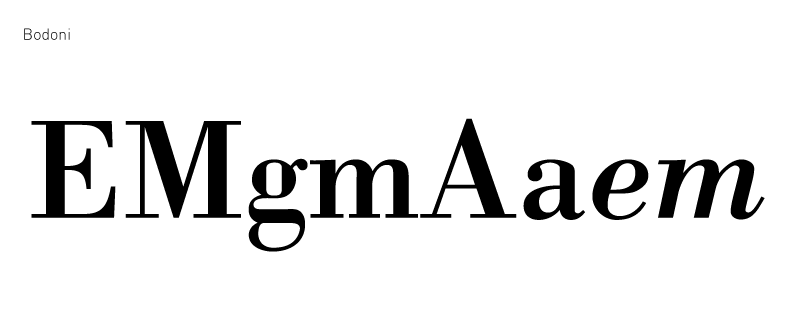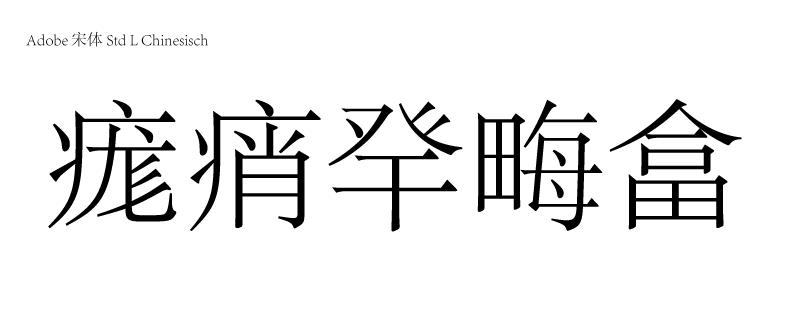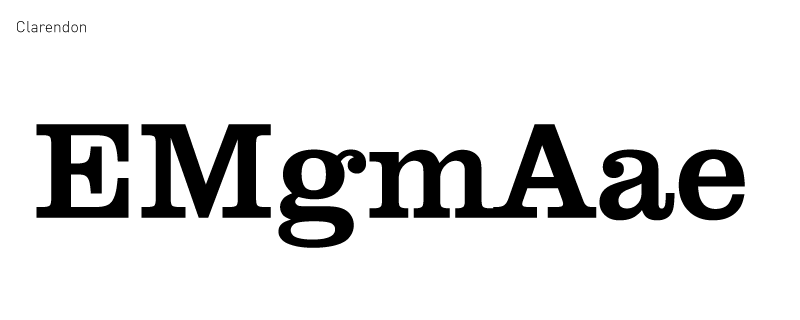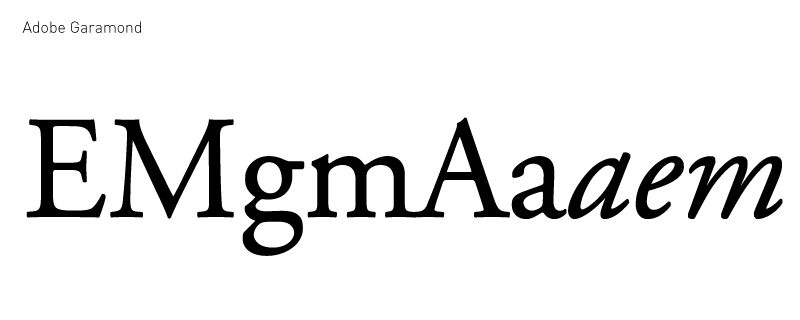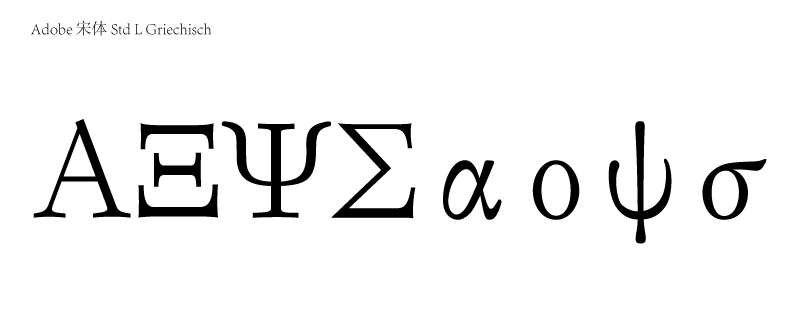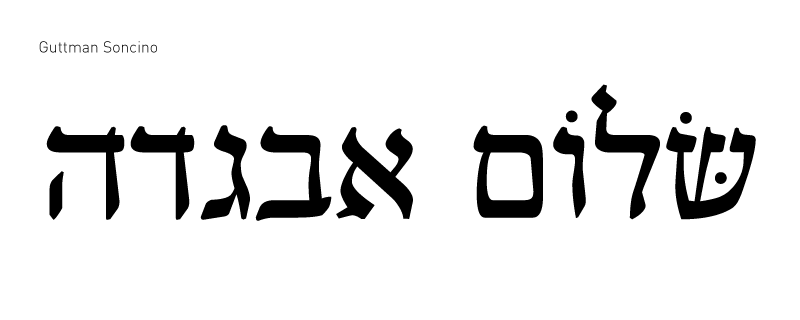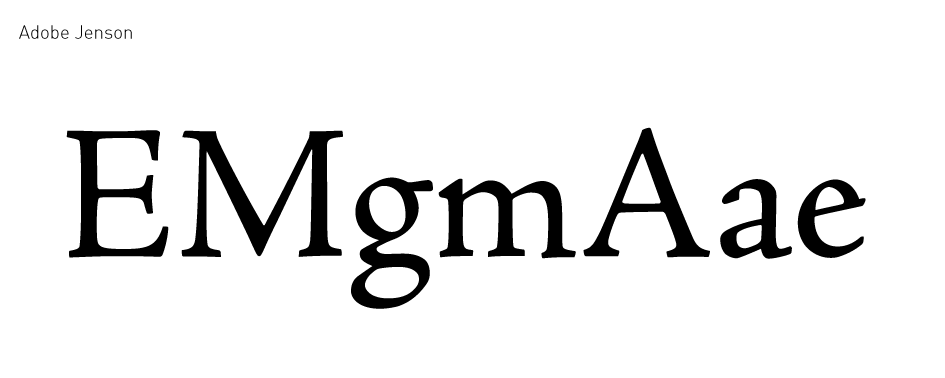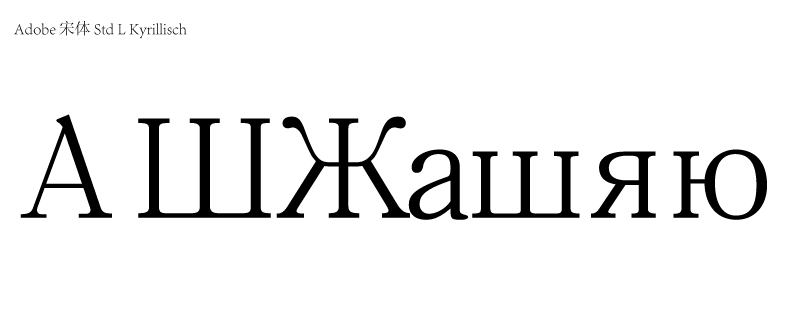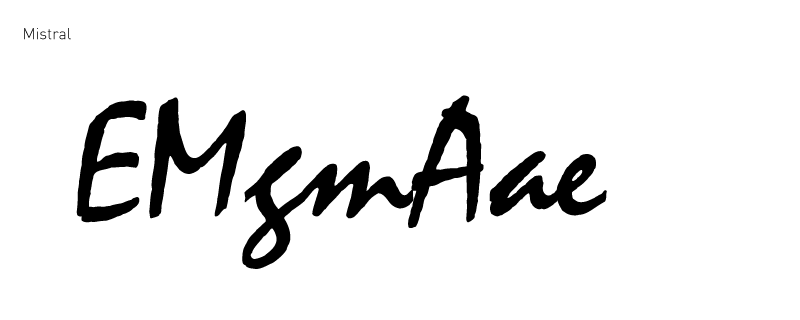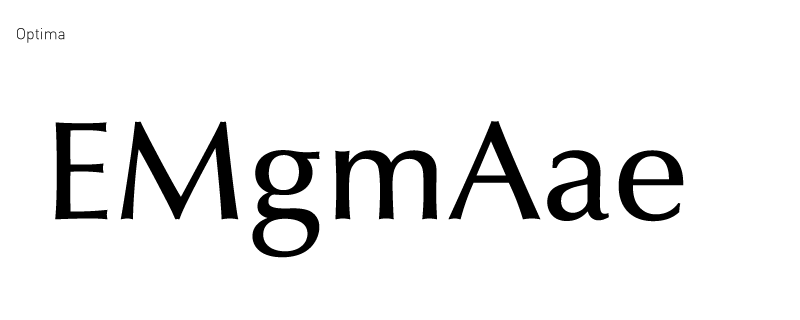
| 1 |
Venezianische Renaissance-Antiqua
|
Schriften
abgeleitet von Formen der frühen Druckzeit
(etwa 1450 bis 1530). Großbuchstaben
basieren auf der römischen Capitalis,
Kleinbuchstaben auf der Humanistischen Minuskel.
Die Schrift zeichnet sich durch kräftige
Serifen, nach links geneigte Achsstellung sowie
relativ große Ober- und Unterlängen
aus, der Querstrich des e liegt meist schräg.
|
Stempel,
Schneidler
|
| 2 |
Französische
Renaissance-Antiqua
|
Schriften,
deren Form im 16. Jahrhundert entstand. Geringe
Unterschiede bei den Strichstärken, nach
links geneigte Achse, abgerundete Serifen, keilförmige
Ansätze an den senkrechten Strichen. Sehr
gut lesbar durch die ruhige Zeilenführung.
Oberlängen der Minuskel meist etwas länger
als die Höhe der Versalien. Ist heute die
Gruppe mit den meisten Schriften.
|
Garamond,
Bembo, Palatino
|
| 3 |
Barock-Antiqua
|
Durch die
Auswirkung des Kupferstichs sind die Strichstärken
unterschiedlicher, die Achse der Rundungen steht
fast senkrecht. Kleinbuchstaben haben meist oben
schräge und unten gerade Serifen. Ebenfalls
sind die Rundungen an den Serifen schwächer
ausgeprägt.
|
Caslon,
Baskerville, Times
|
| 4 |
Klassizistische Antiqua
|
Entstand um
1800, starke Unterschiede zwischen Haar- und
Grundstrichen, waagerecht angesetzte Serifen,
senkrechte Achse bei Rundungen. Kaum Rundungen
am Serifenansatz.
|
Bodoni,
Walbaum, Didot
|
| 5 |
Serifenbetonte Linear-Antiqua (Egyptienne)
|
Früher
Egyptienne genannt, kam zu Beginn des 19.
Jahrhunderts auf. Mehr oder weniger starke, aber
auffallende Betonung der Serifen. Haar- und
Grundstriche sind fast gleich dick.
|
Rockwell,
Clarendon, Serifa
|
| 6 |
Serifenlose
Linear-Antiqua (Grotesk, Endstrichlose)
|
Optisch ist
ein Teil der Schriften dieser Gruppe in der
Strichstärke einheitlich, bei anderen kann
sie sich jedoch auch stark unterscheiden. Heute
umfasst diese Gruppe sehr viele verschiedene
Schriften, die eigentlich eine
Unterklassifizierung erfordern würde. So
basieren einige auf der Klassizistischen
Antiqua, andere auf der Renaissance-Antiqua.
Parallel entstand in den USA die sog.
Amerikanische Grotesk. Zu Beginn des 20.
Jahrhunderts kamen die konstruierten Grotesk
auf, die auf exakten geometrischen Grundformen
basierten.
|
Akzidenz
Grotesk, Univers, Lucida Sans, Syntax, Franklin
Gothic, Futura, Eurostile
|
| 7 |
Antiqua-Varianten
|
Hier werden
alle Antiqua-Varianten einsortiert, die nicht in
die Gruppen I bis III, VIII und IX passen, weil
ihre Strichführung nicht deren Charakter
entspricht. Hauptsächlich finden sich hier
Schriften für dekorative Zwecke.
|
Optima,
Largo, Souvenir
|
| 8 |
Schreibschriften
|
Schriften,
die die Wirkung einer heutigen Handschrift
nachahmen. Es gab sie auch schon zu
Bleisatz-Zeiten, jedoch kamen sie erst durch die
Verwendung auf Computern mehr in Mode.
|
Mistral,
Pepita
|
| 9 |
Handschriftliche Antiqua
|
Schriften,
die auf der Antiqua basieren, die Buchstaben
jedoch handschriftlich abwandeln und so ein
»persönliches« Erscheinungsbild
vermitteln.
|
Post
Antiqua
|
| 10 |
Gebrochene Schriften
|
Nach 1940
kaum noch in Gebrauch, vorher jedoch als
parallele Schriftkultur zu den Antiqua-Schriften
gebräuchlich. Werden noch mal in die fünf
Untergruppen Gotisch, Rundgotisch (Rotunda),
Schwabacher, Fraktur und Fraktur-Varianten
unterteilt.
|
| 11 |
Fremde Schriften
|
Kyrillisch, Griechisch, Hebräisch, Chinesisch